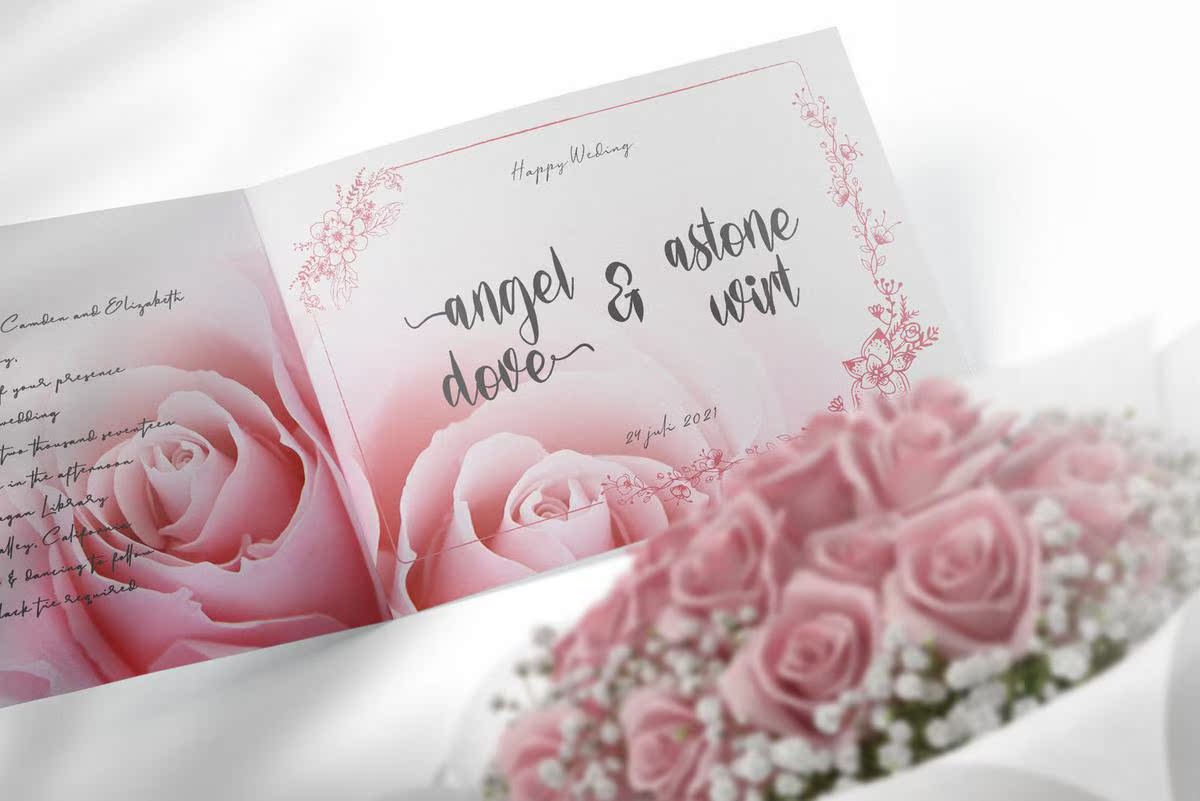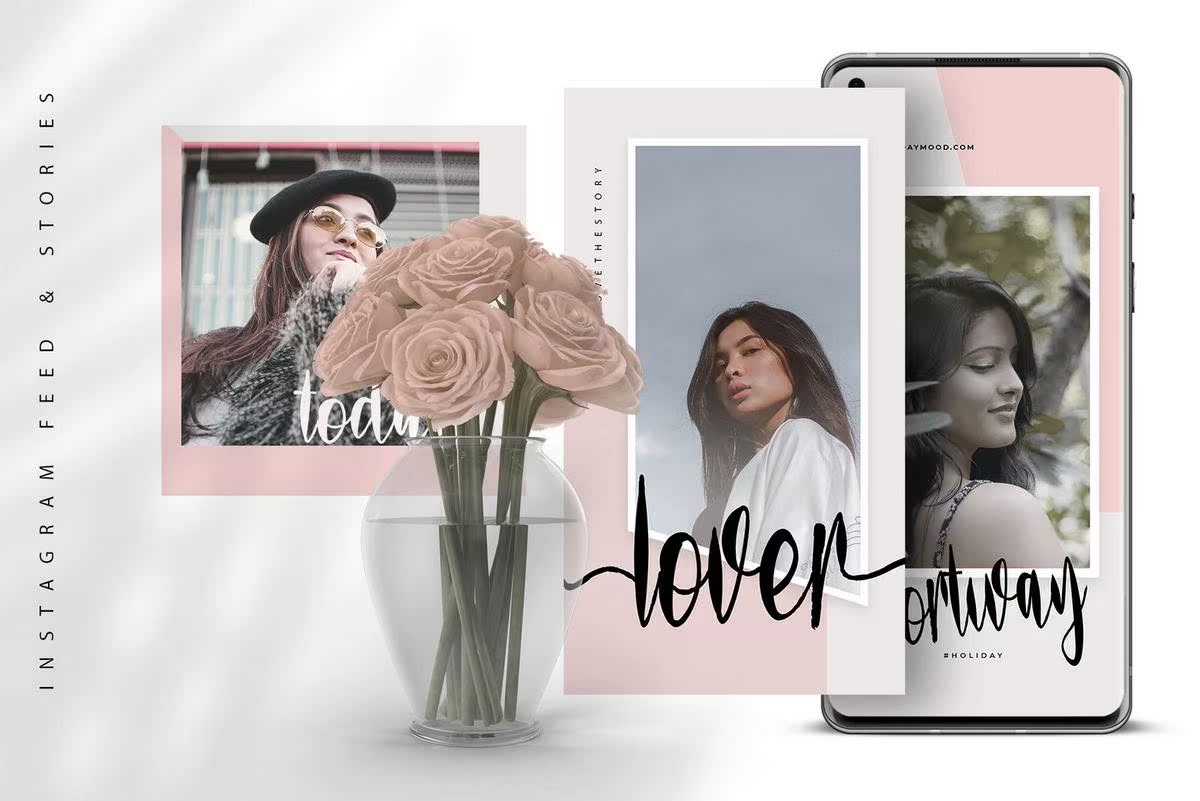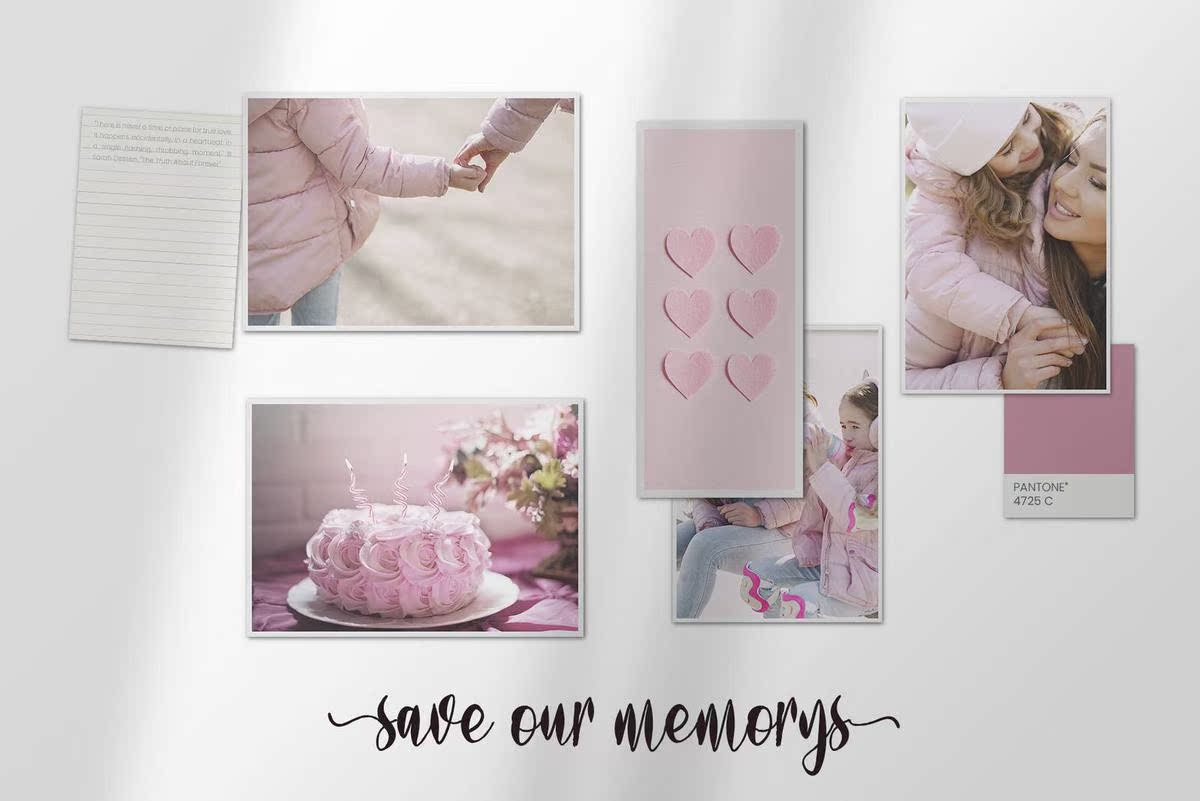
RosepertiWith ScriptFontStyles。适合您项目的文字和数字集合非常适合于标识、品牌设计、标识设计、数字刻字艺术、T恤/服装、海报、杂志、标志、广告设计和任何设计需求。RosepertiWith ScriptFontStyles。适合您项目的文字和数字集合非常适合于标识、品牌设计,标志设计、数字文字艺术、T恤/服装、海报、杂志、标志、广告设计和任何设计需求。